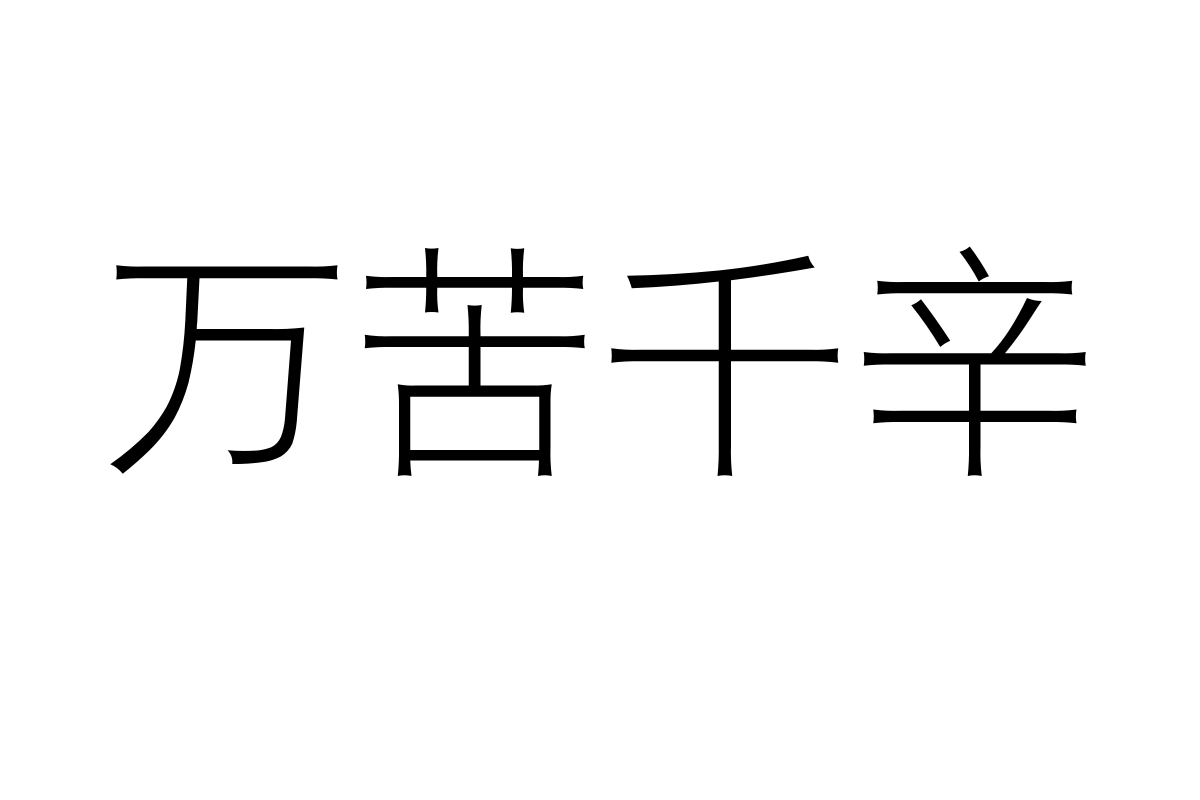
汉仪君黑-35是一款具有现代感和时尚感的字体,它采用了简洁而优雅的设计,适合用于各种商业、广告、设计等领域。这款字体的特点是笔画流畅,字形饱满,给人一种轻松愉悦的感觉。同时,它的可读性也很好,无论是大字还是小字都能清晰可见。此外,汉仪君黑-35还具有一定的艺术感,适合用于需要强调个性和创意的设计中。总的来说,汉仪君黑-35是一款非常实用的字体,值得推荐使用。